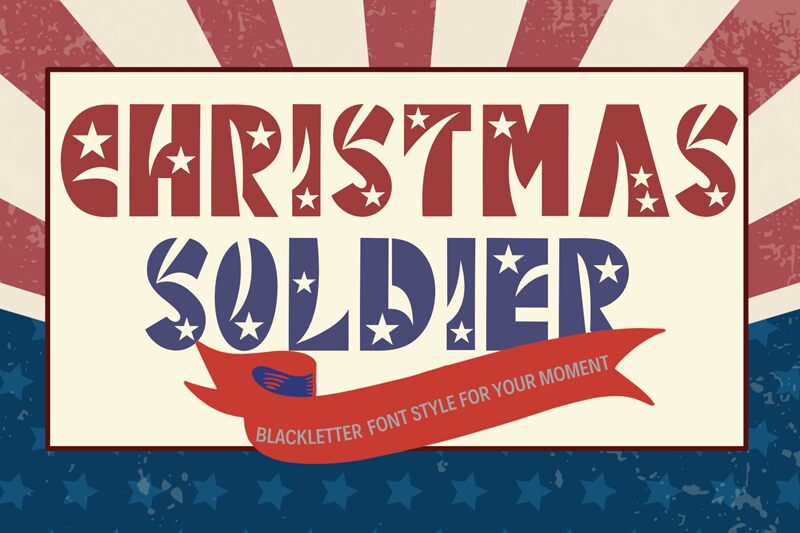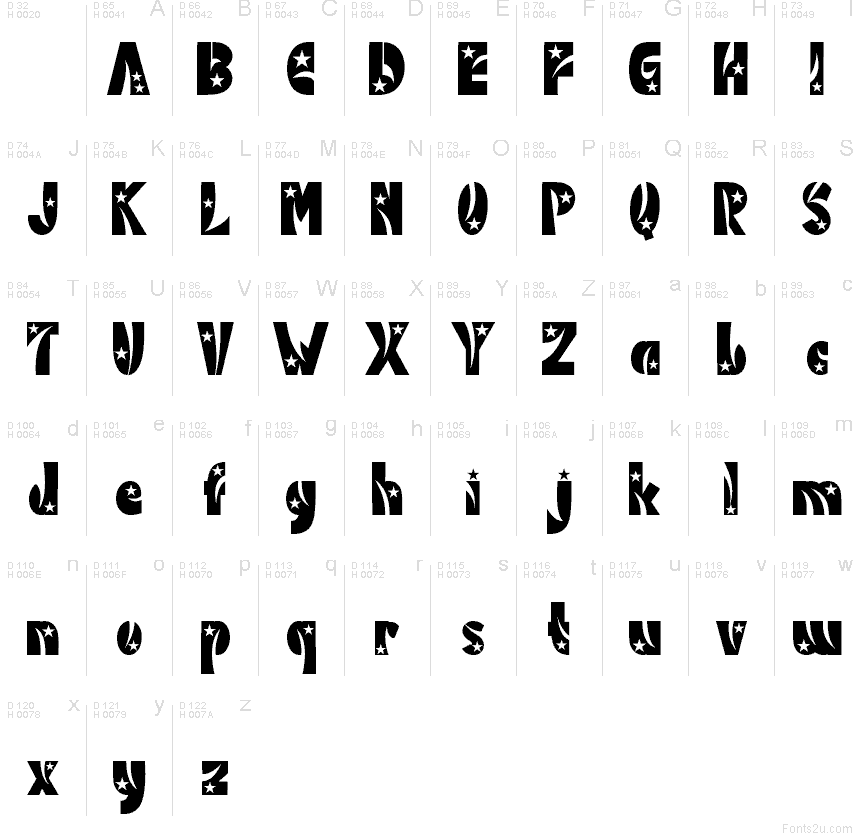
Christmas Soldier de Yoga Letter es una tipografía display navideña que destaca por sus formas robustas, troquelados de estrellas y cortes curvos que confieren a cada letra un aire festivo y artesanal. Sus formas verticales sólidas se combinan con aberturas redondeadas y motivos estelares, creando un estilo decorativo que mantiene la claridad.
Christmas Soldier es ideal para pósteres navideños, folletos de eventos, logotipos de temporada, etiquetas de regalo y tarjetas de felicitación que busquen un impacto visual fuerte. También encaja en banners, layouts de scrapbooking y empaques festivos, ya que la repetición de las estrellas y las curvas integradas mantiene la coherencia temática en todo el diseño.